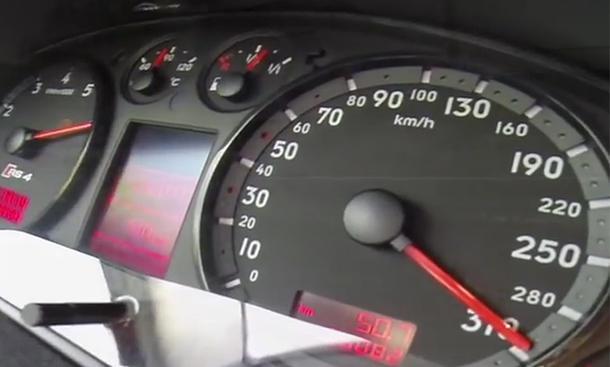
Audi Tacho-Schriftart
Hallo Ihr, ich hoffe ihr könnt mir helfen. Bin schon seit längerer Zeit auf der Suche nach der Schriftart des Tachos. Ich weiß das Bild ist nicht gut, leider habe ich kein anderes. Hat jemand eine Idee welche Schriftart das sein kann oder zumindest eine ähnliche? Ihr würdet mir sehr weiterhelfen. Danke
Sieht aus wie eine DIN- oder (noch besser) Highway-Schrift - bis auf "Null" und "Neun" passt diese Schrift - aber vielleicht erster Anhaltspunkt für die Suche.:
Normalerweise nutzt Audi seine Hausschrift "AudiType" für den Tachometer ...
Ihr Tachometer stammt aus einem RS 4, ähnelt dem des RS 6 plus aus dem Jahr 2004 (www.autobild.de/artikel/audi-rs6-plus-45535.html, da gibt's auch in der Bildergalerie ein Foto vom Tacho  ;-)). Da hat Audi als Hausschrift noch eine von Metadesign aufpolierte "Univers Extended" genutzt, die "AudiSans" genannt wurde (http://www.fontblog.de/typografischer-relaunch-bei-audi/). Vielleicht mal nach der "AudiSans" im Netz suchen? Seit 2009 wird in den Tachos nur noch die "AudiType" genutzt.
Die Beschriftung der S- und RS-Tachos war schon immer von der der anderen Modelle abweichend, die AudiSans wurde damals dafür nicht verwendet.
Hm, stimmt, die 3 passt nicht zur Univers. Würde wie gesagt auf so eine Art Highway- oder DIN-Schriftart tippen - bei der Interstate z.B. sieht das kleine "L" mit der abgeschrägten Spitze ein wenig wie die "1" im Tacho aus. Allerdings passt die "3" nicht ...
Würde sagen: Treffer! Offenbar hat Audi das große "i" als "1" genutzt, passt auch irgendwie nicht wirklich zu den anderen Ziffern. Aber das ist sie definitiv :-))